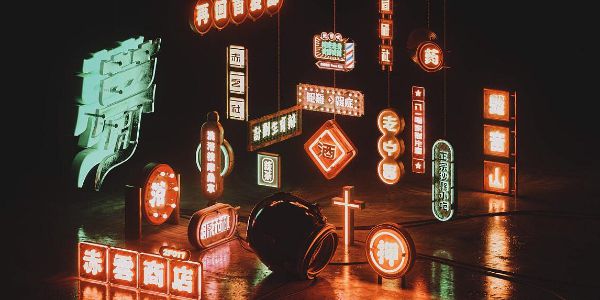
他并非专业出身,却将字体设计玩到了极致!
尘,"Chen" :Dust
港,"Gang" :Harbor
東,"Dong" :East
影,"Ying" :Shadow
颤,"Chan" :Tremor
叠,"Die" :Stack
翻,"Fan" :Turn
開,"Kai" :Open
刃,"Ren" :Blade
撕,"Si" :Tear
压,"Ya" :Pressure
癌,"Ai" :Cancer
盲,"Mang" :Blind
生,"Sheng" :Produce
飘,"Piao" :Float
音,"Yin" :Musical note
摇,"Yao" :Swing
除了动态字体,他最开始是以一组许巍的字体海报,获得超高人气的。
这系列作品,还入选了全球最佳图形设计杂志《Gallery - the world's best graphics》。
受邀许巍重庆音乐会展览~
可以说是非常优秀了,不过这还不算完,他还设计过美术字系列。
(三维设计来自灰昼)
以及为商业项目设计的logo字体,其中不乏你耳熟能详的大品牌。
真正是爱字体的大神了,行行珂之所以有这么多的汉字玩法,离不开他探索和挖掘新事物的习惯。他曾经观察过水滴的形状,并将其融入字体设计中。所以它的作品是有灵性的,每个细节都来源于生活,并加入了自己的思考。
众生相
碎x圆
赌
无神论
世界杯
空
坠落
不要依赖别人,你可以依赖的只有你自己。
不要停止练习的脚步,即使你觉得用处不大。
不要事事提问,学会独立思考。
不要沉迷于技法,想法更重要
不要抄袭,抄袭会上瘾。